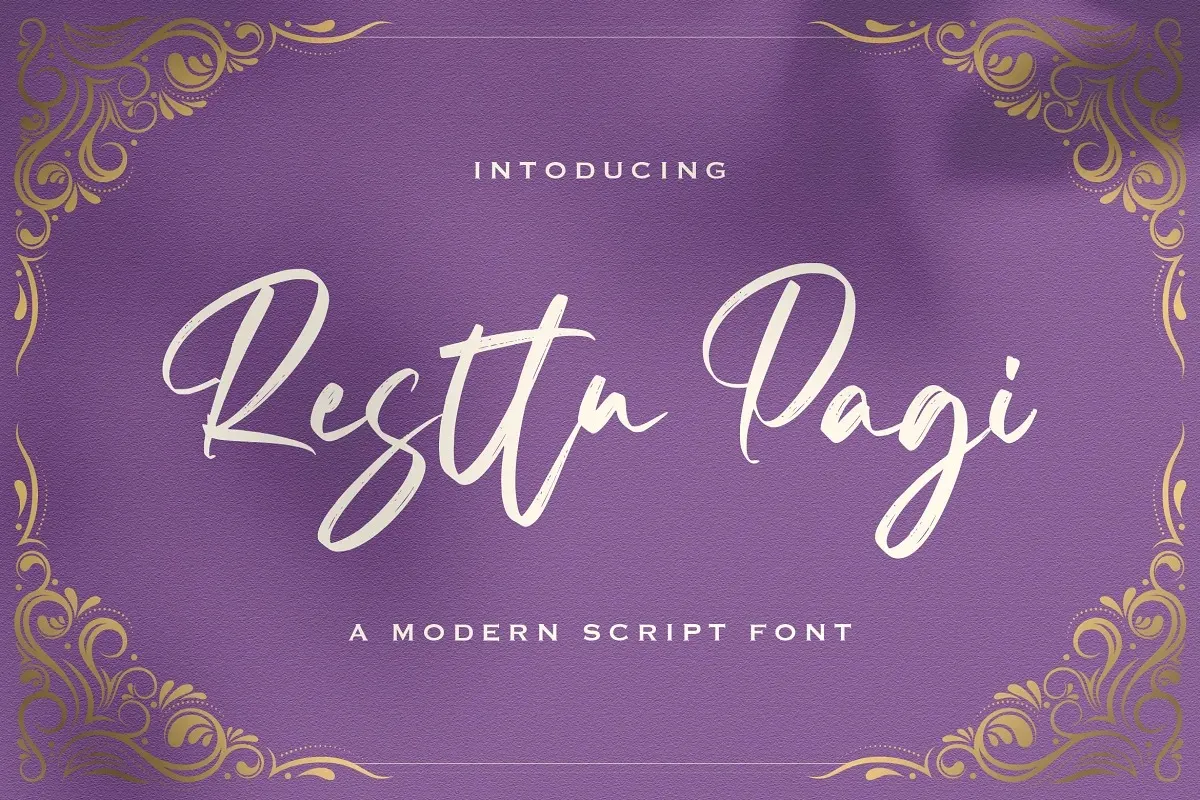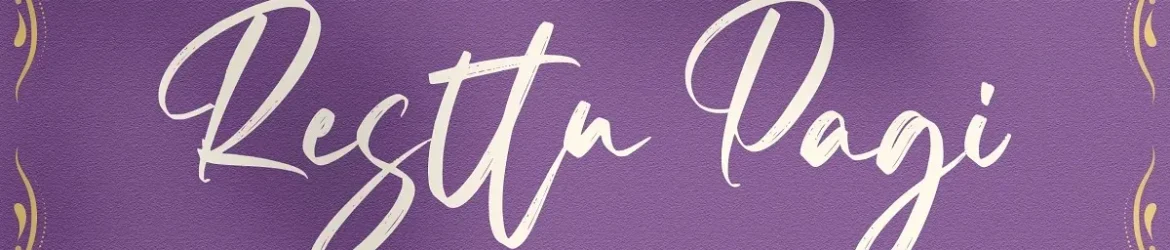
A fonte ‘Resttu Pagi’ é uma escolha perfeita para aqueles que buscam uma combinação única de elegância e casualidade. Inspirada nos traços delicados do script, esta fonte foi criada pelo designer 99designs para um público diversificado. Com linhas equilibradas e texturas únicas, a ‘Resttu Pagi’ traz um toque especial aos projetos mais audaciosamente imaginativos, tornando-os ainda mais vibrantes e autênticos. Esta fonte é perfeita para designers que desejam adicionar um charme especial a seus trabalhos, seja em texturas de letras ou em layouts criativos. Com ‘Resttu Pagi’, os projetos ganham uma personalidade única sem perder a legibilidade. É ideal para uso tanto na tipografia como nos elementos gráficos do seu projeto, oferecendo um toque de sofisticação e originalidade que certamente marcará sua marca entre outros designers.